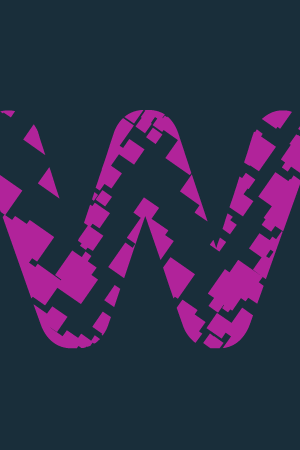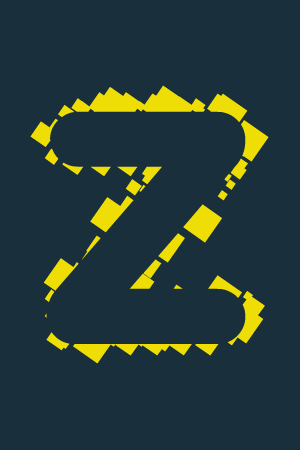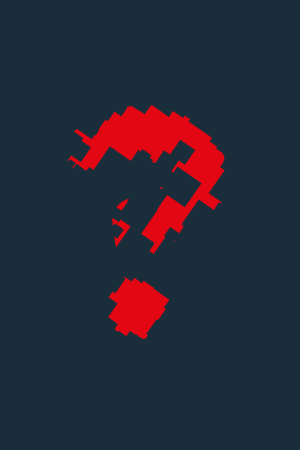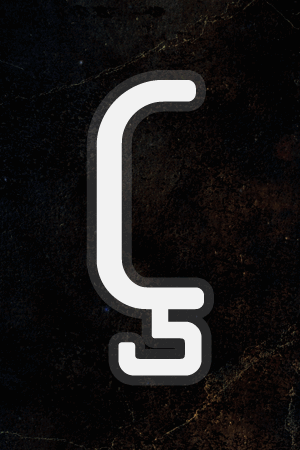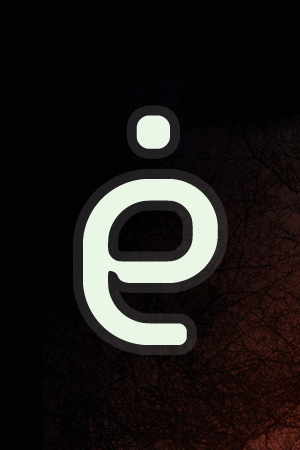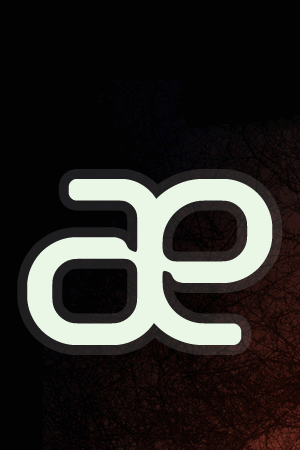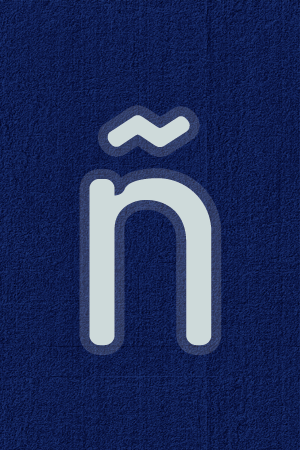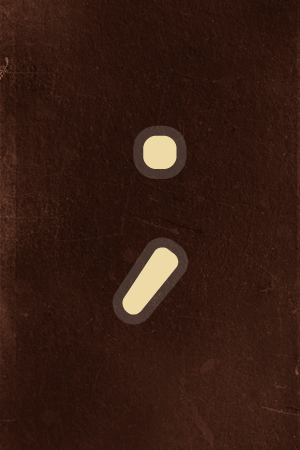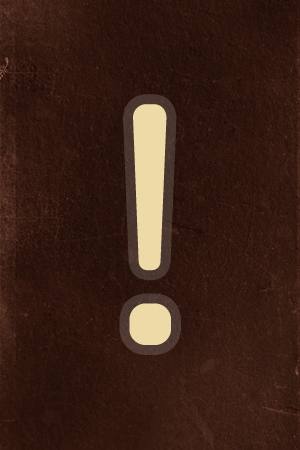
La chata, tipografía & webfont gratis
«La chata»
Esta es una tipografía de palo seco uniforme, con acabado redondeado en las terminaciones de las astas, ápices, vértices, colas o espolones, también en las uniones con el asta de los travesaños, barras y hombros.
Actualmente sigo desarrollando esta tipografía para su uso en auto-edición y en formato Open Type, con más caracteres, ligaduras, símbolos y letras alternativas (+ en Quark Xpress e Indesign), así como las versiones Bold e Itálica, posteriormente me gustaría extender la familia con otros pesos y medidas, pero dado el tiempo que lleva el diseño de una fuente, no tengo claro cuando lo tendré listo…
La idea de desarrollar esta tipografía para la web surgió a principios de 2011 con motivo del rediseño de mi logotipo e imagotipo, como expliqué en el post: “Un logo, un pez y otro pez“; pero el deseo de diseñar una tipografía completa viene de más atrás, y sólo ahora, lo he podido ver hecho realidad.
Comencé con gran entusiasmo el dibujado de las letras, ya tenía 7! (defharo), primero definí la altura de las mayúsculas, de los ascendentes y descendentes, continué dibujando frenético, con Freehand, letra a letra, cuando tuve todas las mayúsculas, minúsculas, números y signos de puntuación me fuí a Fontlab para compilar la fuente, lo hice de una manera intuitiva, digo intuitiva pues no conocía el programa ni tampoco los conceptos a tener en cuenta en el desarrollo de una fuente, establecí a ojo el espaciado de caracteres, pasé por encima del kernig y le di al menú “Generate font..”, emocionado, instalo la nueva fuente y corriendo voy a QuarkXpress, compongo un largo texto de 12pt con “La chata”, vaya, parece que en pantalla, con el zoom activado todo se ve bien, eureka!!..
Imprimo un par de hojas con los párrafos, espero ansioso que la impresora “escupa” la hoja, ya está, cojo con emoción el resultado y comienzo a leer el texto… sólo bastaron unos segundos para llegar a la conclusión que era muy dificil la lectura, las alturas, los espaciados, la coherencia morfológica, etc… todo mal!! de una manera intuitiva, cegado por la emoción del dibujo de las letras, sin método, sin planificación y sin conocimientos suficientes sobre los intríngulis del diseño de fonts, el proyecto parecía insalvable.
Llegué a la conclusión que debía conocer más sobre la técnica del dibujado tipográfico y sobre el programa que facilita esto, encontré un breve, pero muy útil, manual de Fontlab, a partir de los consejos incluidos aquí me dispongo a corregir errores y sobretodo me centro en el espaciado de caracteres e interlineado, pensando que sólo de ahí derivaba la falta de legibilidad de la fuente, paso muchas horas conociendo el funcionamiento de estas técnicas, establezco decenas de pares de letras, vuelvo a imprimir, bueno, parece que algo a mejorado, pero los textos continúan siendo muy dificiles de leer, es una tortura intentarlo con una cierta velocidad… me paro, observo letra a letra, entorno los ojos… no hay uniformidad!!, muchos fallos en el dibujado de las letras y medidas sin método.
Sigo los consejos del manual de Fontlab y me dispongo al redibujado de todos los caracteres, elimino y modifico nodos según los consejos aprendidos (ortogonalidad), establezco los patrones para el trazado de todas las curvas, geometrizo hasta la extenuación, a la par, encontré el manual en español de typeTool, la versión light de FontLab, es indispensable para mi conocer los pormenores de la herramienta, leo incansable, con nocturnidad y alevosia el manual de 420 páginas, aprendo muchas cosas y entiendo muchas más, deseo que llegue el nuevo día para aplicar lo aprendido.
Por fin, tengo compilada una nueva versión de la tipografía con 720 glifos, 1800 pares de letras definidos para el kerning, un nuevo espaciado de palabras, cantidad de letras alternativas y más de 200 horas a la espalda, ahora la lectura ha mejorado considerablemente, aunque todavía hay letras que se pueden mejorar…
Después de 2 semanas embarcado en otros trabajos, retomo la edición de la fuente, hay algo que todavía me inquieta y no se que es, pienso en que sería bueno comparar el resultado, no lo había vuelto a hacer, con mi logotipo, cual es mi sorpresa al observar que las terminaciones de las astas, ahora semicírculos perfectos, han perdido la esencia y la gracia de los originales, donde estas curvas son achatadas, no me lo pienso dos veces y comienzo el 3er redibujado de la fuente, es en este momento que elijo el nombre de la fuente “La chata”, por fin me decido a hacer una versión simple que incluye 391 caracteres, los suficientes para el uso con todos los idiomas europeos, rediseño algunas letras que estaban “medio perdidas”, investigo sobre las llamadas webfonts y me decido finalmente a poner la tipografía para descargarla gratis, ya que, actualmente mediante @font-face es posible usar fuentes personalizadas en el diseño web. En el archivo encontrarás la fuente en varios formatos y un html de ejemplo con la hoja caracteres aplicados en la web.
La historia continúa… he subido esta fuente para descarga a Dafon.com y estoy contento con la respuesta en descargas; también envié la fuente para incluirla en Google fonts, jajaja! iluso y precipitado de mi, me la rechazaron amáblemente diciendo que no cumplia con la calidad esperada, recomendándome subir la fuente a la Open Font Library y esperar la ayuda de alguien para corregir todavía no se que, este es el drama y el reto, aunque tengo algunas sospechas pero voy perdido, en fin, como buen optimista veo oportunidad en mi ignorancia :) hasta pronto.